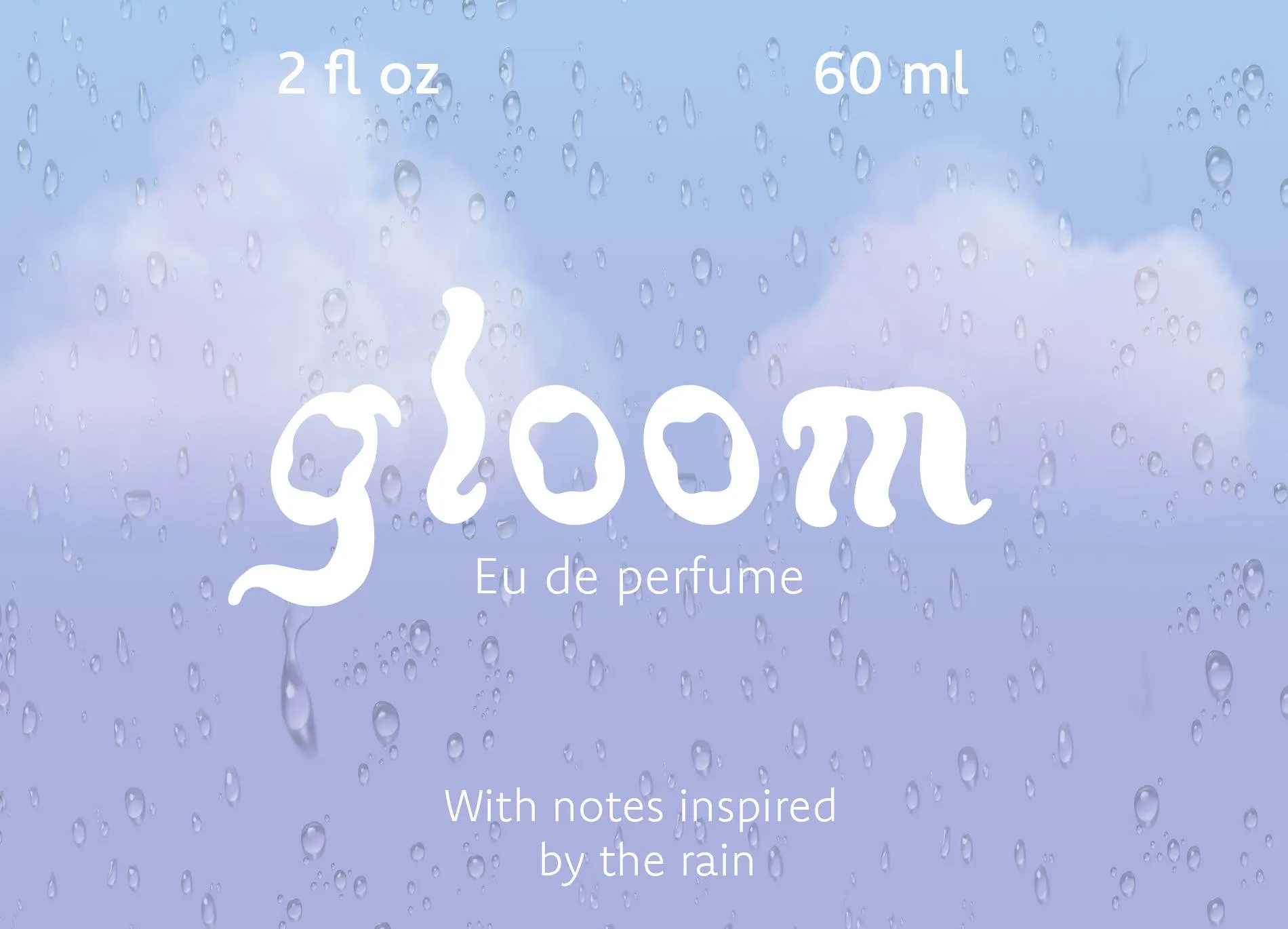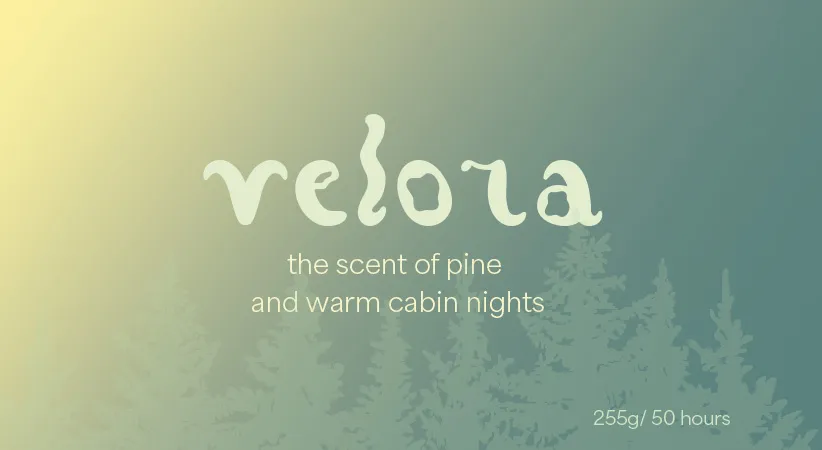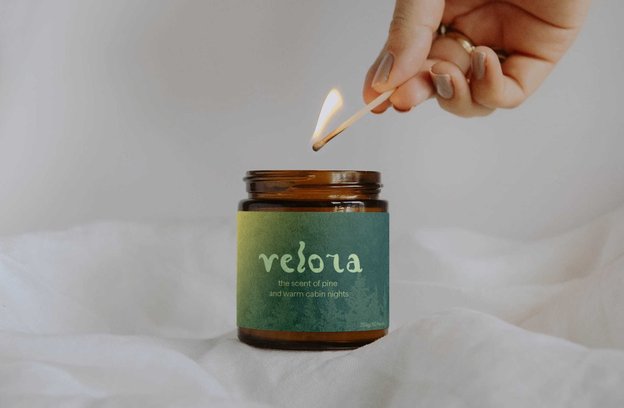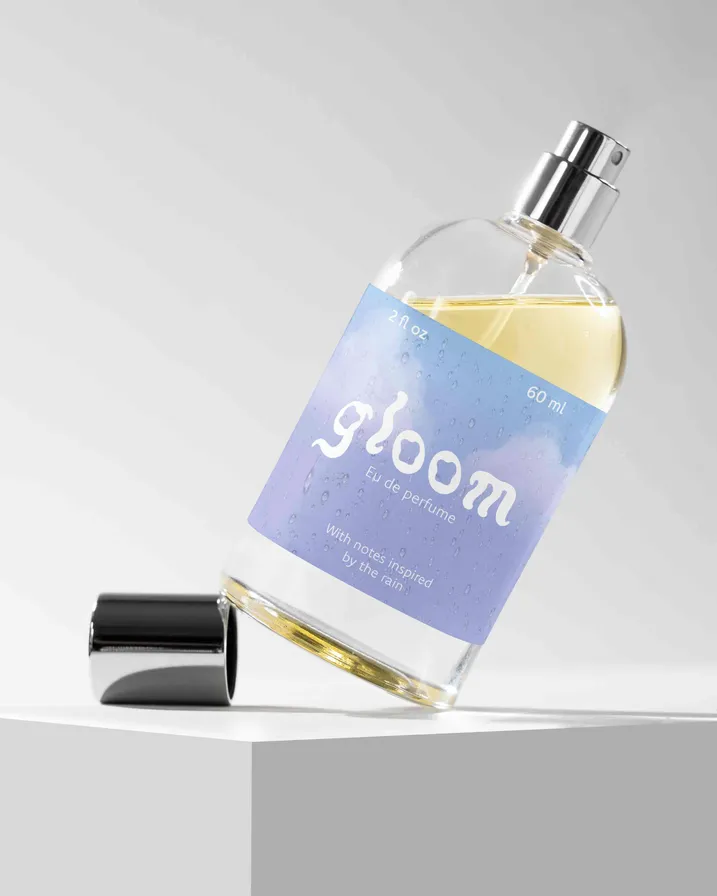
Tipografía Ventopía
Stine Munkas Borresen
Pilar Terrón López
El objetivo fue crear una tipografía con mucho movimiento y formas orgánicas. Me inspiré en elementos naturales como ramas, viento y olas, así como en aspectos humanos como la danza, la arquitectura fluida y el sentido de comunidad. Estas influencias se reflejan en las formas curvas y dinámicas de las letras.